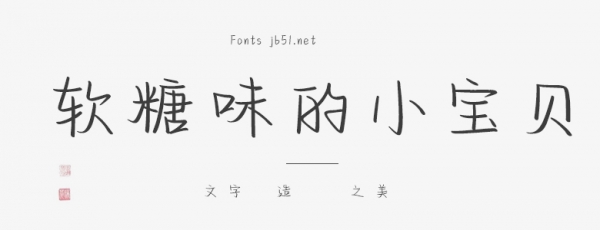
软糖味的小宝贝是一款独特而充满趣味的字体,它拥有迷人的甜蜜感,仿佛是一颗颗色彩斑斓的软糖,充满了童年的欢乐与纯真。 这款字体的设计灵感来源于儿童绘画的笔触,每一个字母都带有手写痕迹,充满了生动的气息。字形圆润可爱,线条流畅,给人一种亲和力十足的感觉。 软糖味的小宝贝在细节处理上非常出色。特别在字母的起笔和收笔处,设计者都精心地加入了小圆点,宛如小朋友们习惯性留下的可爱小手印。而在部分字母的转折处,则运用了优美的曲线,使得整个字体显得更加流畅自然。 在整体视觉感受上,软糖味的小宝贝给人一种欢快、轻松的氛围。这款字体充满了玩味性,适合应用于儿童节、幼儿园、儿童书店等相关领域的品牌和产品设计中,定能吸引小朋友和大人们的目光。 总之,软糖味的小宝贝是一款充满童趣和个性的字体,它将为您的设计作品增添一抹亮丽的色彩,让您的作品更具吸引力。